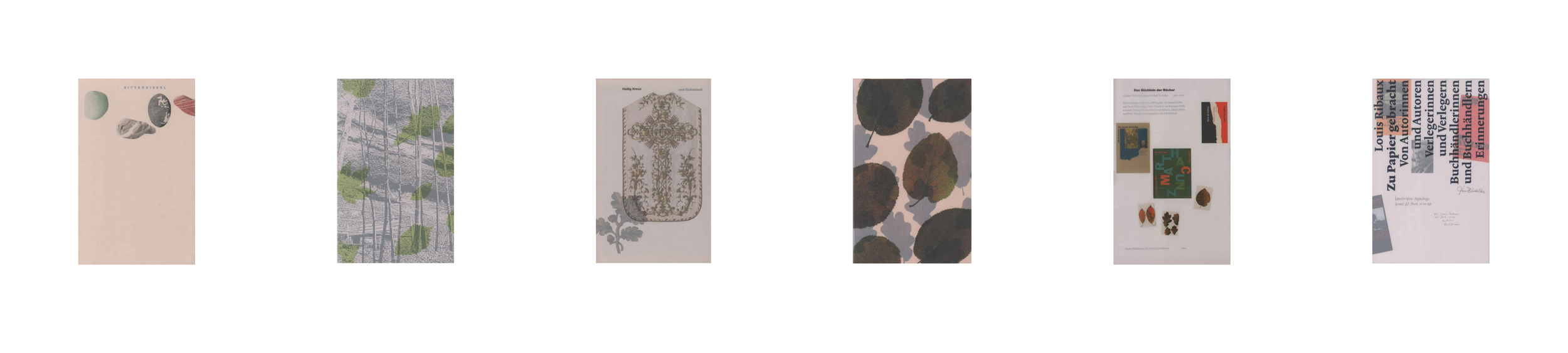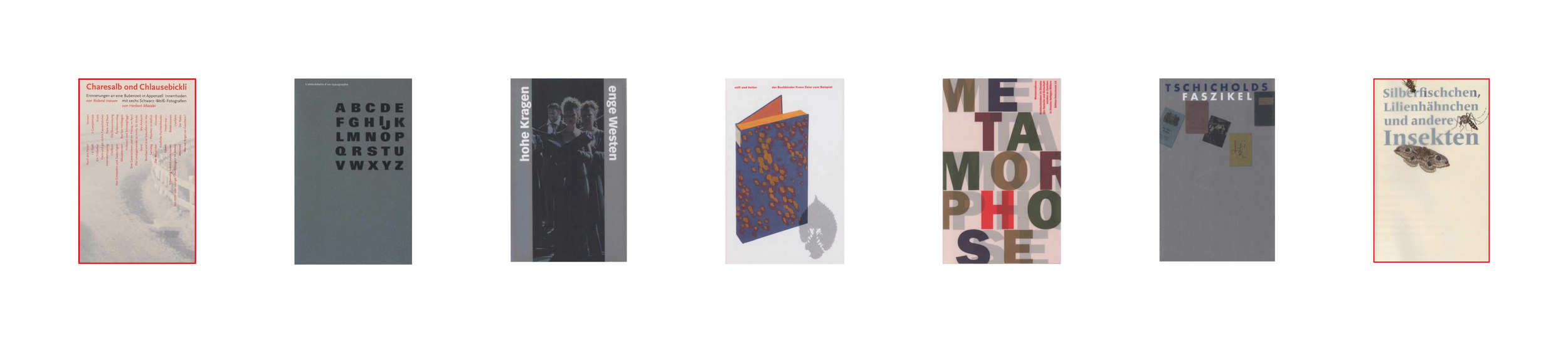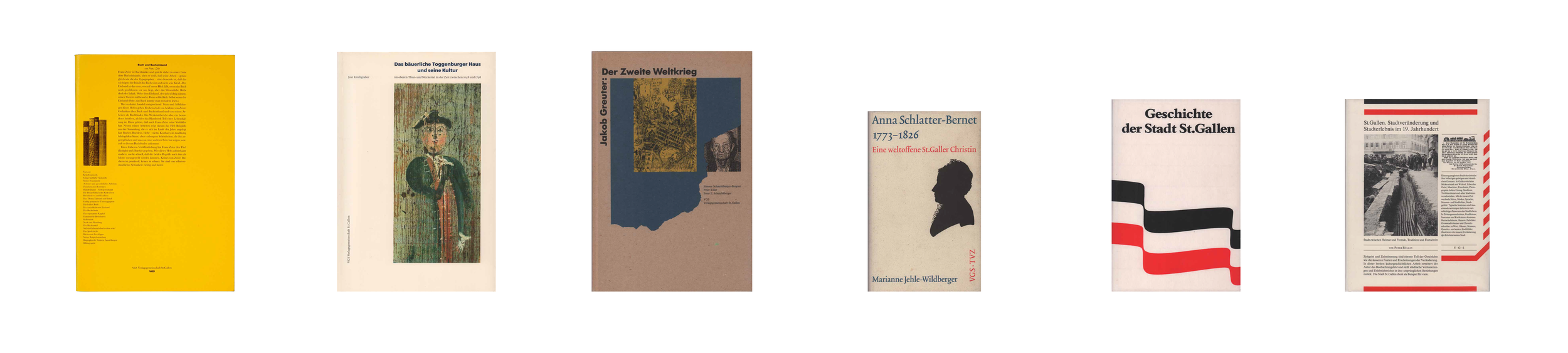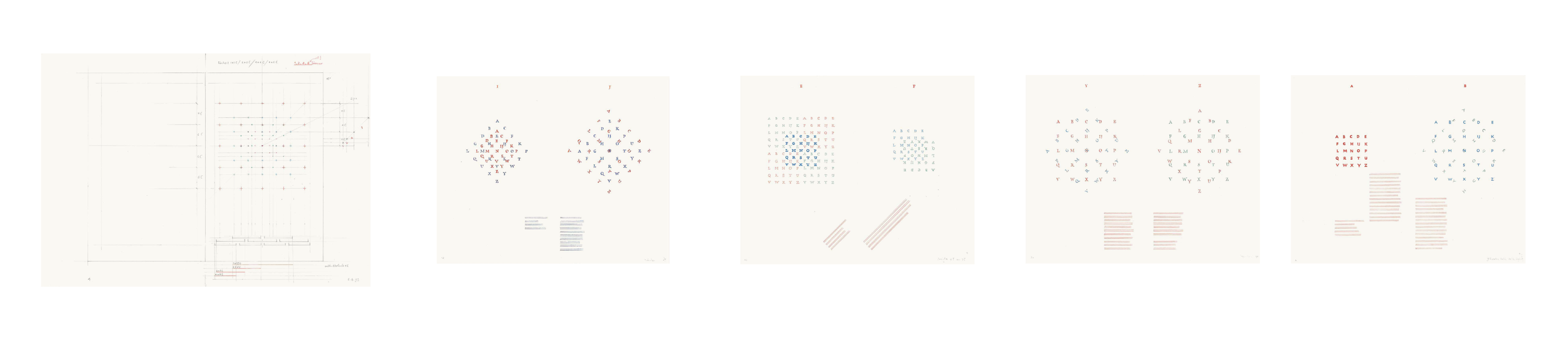
Jost Hochuli– Typobiografie
Typobiografie. Jost Hochuli: Arbeiten aus 60 Jahren
Typobiography. Jost Hochuli: the work of 60 years
9. November bis 7. Dezember 2025: Transtage, Hangzhou, China
Eine Ausstellung mit den Werken Hochulis wird am 9. November 2025 im Zentrum Transtage in Hangzhou, China, eröffnet. Kuratiert von Zhang Midi, Yu Qiongjie und Wang Yanru, wird die Ausstellung organisiert von Transtage und Yushutang und unterstützt von Founder Type, Study Group und The Type. In Zusammenarbeit mit der School of Visual Communication an der Chinesischen Akademie der Künste wird Jost Hochuli einen Online-Vortrag halten, während Roland Stieger bei der Eröffnung anwesend sein und an der Akademie der Künste ebenfalls einen Vortrag über Hochulis Arbeiten halten und einen Workshop führen wird.
Die Ausstellung ist Teil einer Reihe mit dem Titel Modern Typography Research. Diese Reihe versucht, die Entwicklung moderner Typografie zu verstehen, indem die Werke repräsentativer und einflussreicher Gestalter untersucht, klassische Designkonzepte bekannt gemacht, berufliche Tradition beachtet und zukünftige Entwicklungen gefördert werden. Seit 2021, mit der Ausstellung Typographic Composition, Yoshihisa Shirai, werden die Ausstellungen regelmässig von einer Publikation begleitet, im Juni 2024 erschien als zweite Veröffentlichung der Reihe die chinesische Version von Hochulis Systematische Buchgestaltung?
Nachdem bereits 2023 die deutschsprachigen, englischen, französischen und italienischen Ausgaben von Jost Hochulis Typobiografie erschienen waren, ist dieses bedeutende Werk seit Oktober 2025 im Hunan Fine Arts Publishing House auch auf Chinesisch erhältlich. Das Buch ermöglicht einen Überblick über Hochulis Arbeiten aus 60 Jahren – Bücher zur Hauptsache, aber auch Plakate, Signete, Entwurfsreihen und Konstruktionsblätter, eine auf den Beruf fokussierte Autobiografie, Texte anderer Autoren und eine vollständige Bibliografie.
Der englische Designer Norman Potter betont in seinem Werk What is a designer, man sollte Arbeiten von Designern mit eigenen Augen und Händen erkunden (with one's own hands and eyes). Zur Publikation der chinesischen Ausgabe der Typobiografie erarbeiteten wir eine Ausstellung mit dem gleichen Titel. Sie zeigt Hochulis Bücher und wie im Buch auch andere grafische Arbeiten sowie Skizzen und Entwürfe. Die meisten Exponate hat Zhang Midi über die Jahre für sich gesammelt, nur wenige mussten für die Ausstellung von Hochuli zur Verfügung gestellt werden. Die Originale der Skizzen und Konstruktionsblätter, die nicht verschickt werden konnten, sind in hochaufgelösten Repros und in originaler Größe vorhanden und werden hier zum ersten Mal öffentlich gezeigt. Alle Bücher können in die Hand genommen und durchgeblättert werden – so, wie es Potter verlangt. Speziell für diese Ausstellung hat Hochuli auch ein Vorwort geschrieben und die Kuratoren organisieren Lese- und Diskussionsrunden, wofür sie verschiedene chinesische Designer eingeladen haben.
Diese Reihe versucht, die Entwicklung moderner Typografie zu verstehen, indem sie die Werke repräsentativer und einflussreicher Gestalter untersucht und sich im Übrigen mit allen Aspekten der Typografie beschäftigt.